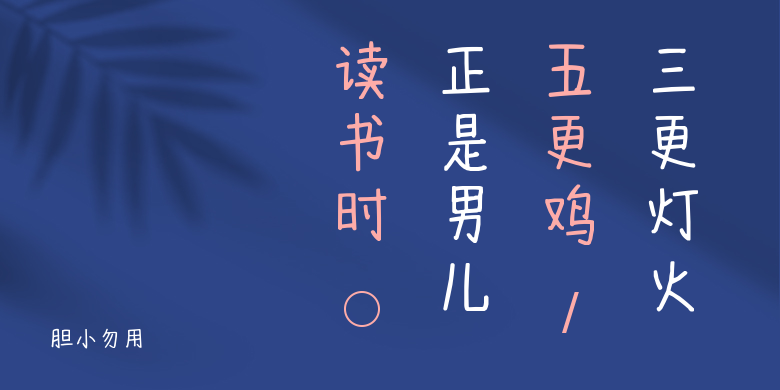
胆小勿用
胆小勿用,这款字体结构工整、笔画清晰,兼顾美观与易读性,适用于标题、正文、海报、包装、LOGO 等多种场景。字形优雅稳定,风格百搭耐看,适配日常排版与创意设计,让文字呈现更舒适、更具质感。胆小勿用一笔一画,皆是细节,以均衡的比例、流畅的线条打造舒适视觉体验,字形端正大气,风格简约现代。无论是商业设计、品牌宣传还是日常排版,都能轻松驾驭,让文字更有格调与力量。胆小勿用字体下载。